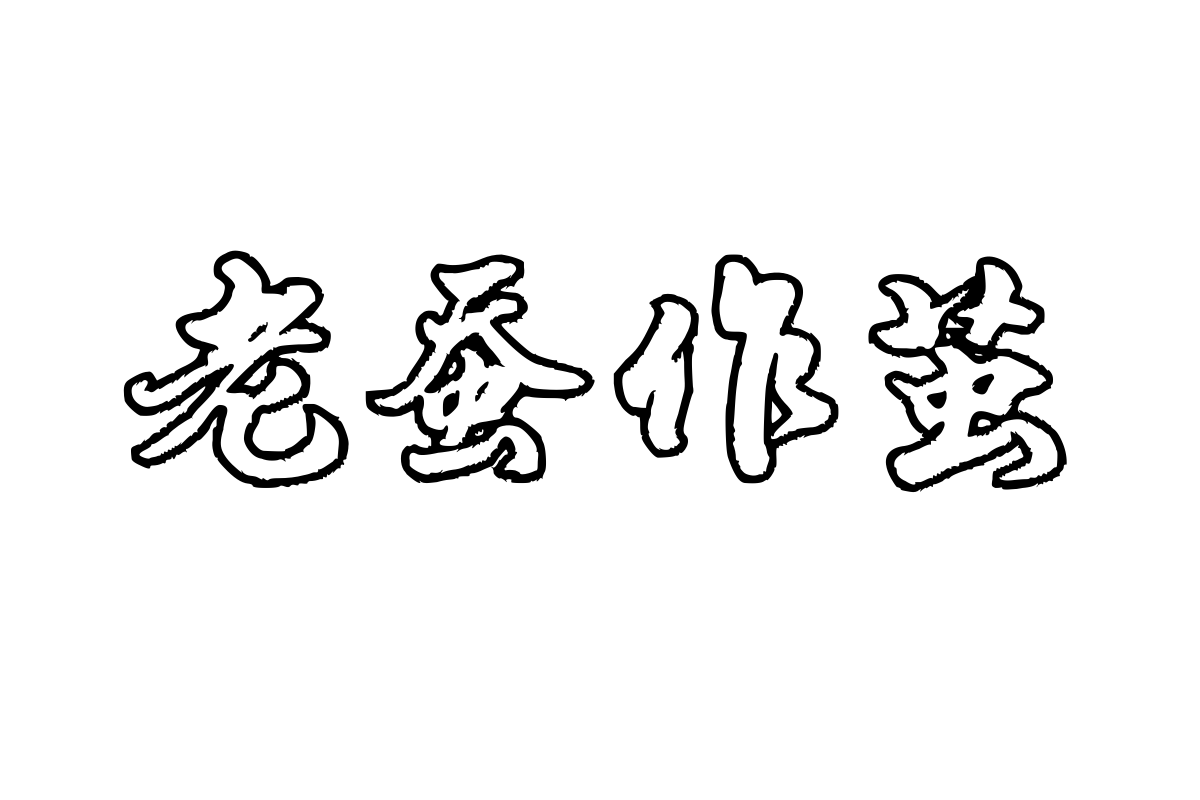
汉呈王天喜空心体是一款现代中文字体,由汉呈科技设计。这款字体以其独特的空心效果而闻名,使得文字在视觉上更加突出和引人注目。
汉呈王天喜空心体的特点在于其笔画的空心效果,这种效果使得文字在视觉上更加醒目,能够吸引人们的注意力。同时,这款字体也具有优雅的线条和流畅的书写风格,适合用于各种商业、广告和设计项目。
总的来说,汉呈王天喜空心体是一款非常适合用于现代设计项目的文字字体,无论是在网站、海报还是其他媒体上,都能够展现出其独特的魅力。